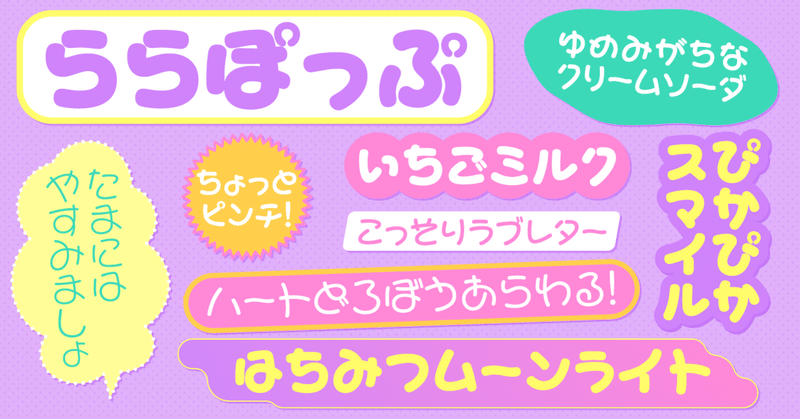
社会現象になった “丸文字” をルーツに持つ書体「ららぽっぷ」
1. 遊び心に溢れたデザイン
ららぽっぷはこんなデザインの書体です。
ららぽっぷは「新丸ゴ」の漢字と組むことを想定して作られた丸ゴシック系かな書体で、新丸ゴに合わせてL・R・M・DB・B・H・Uの7ウエイト展開をしています。(かな書体についてはこちらの記事をご覧ください!)
独特の崩し方をした骨格をもち、遊び心に溢れたかわいらしいデザインをしています。
細かい特徴を見ていきましょう
・有機的な曲線で構成されていて、丸い
全ての文字が直線を含まず、手書きで書いたような揺れのある曲線で構成されています。全体的なシルエットも丸く作られていて、かわいらしさを演出しています。
・ループが大きい
ループを持つ文字は、それが大きく強調されています。文字により丸い印象を与えていますね。
・独特な点の交差
本来接触しない点や線が他のパーツと交差していたり、突き抜ける線が短く接触しない形になっているものがあります。独特の崩し方を感じさせる要素のひとつです。
特徴、掴めてきましたか?
2. ルーツとなった社会現象 “丸文字”
ららぽっぷは2007年にリリースされた書体ですが、この独特の字形は1970〜1980年代に流行した “丸文字” という書き文字のスタイルを意識して作られた書体です。
1970年代後半から、女子学生の間で扁平で丸っこい、癖のある図形的な文字を書くことが一大ブームとなりました。ひらがなの丸い部分を強調したり、角のある部分を丸くして書かれることが多かったことから丸文字と呼ばれます。
当時丸文字を書いていたという弊社スタッフに、再現してもらいました。
それぞれの文字に丸を強調するような特徴があってかわいいですね...!(書いてくれたスタッフはデザイナーではない、というのもミソです)
当時流行していた交換ノートを中心に使う人が増加していき、500万人近くが丸文字を使用していたとも言われるほどです。「かわいい」や「女の子」の象徴として、社会現象になりました。
書体の世界にもその影響は押し寄せ、丸文字だけのデザインコンテストが行われ、入賞作品が書体化されたり、人気アイドルが手書きした丸文字が書体化されるなどしました。デザイナーではない人たちがタイプデザインをしていたと考えると、その影響力がどれほどだったのか考えさせられますね。
モリサワからも、丸文字を元にした書体がリリースされています。
現在はスマホの普及などから文字を “打つ” ことが多くなっていますが、1970〜1980年代は文字を “書く” ことが中心の文化だったとも言えます。その中で書き文字である丸文字が、人々の一種の自己表現にとどまらず、デザインの世界にも影響を及ぼしました。
3. 「ららぽっぷ」デザイナーインタビュー
ここからは、そんな特徴的な背景とデザインを持つららぽっぷの制作秘話に迫るべく、担当デザイナーへのインタビューをお届けします!
お話を聞いた人:タイプデザイナー 市川秀樹
プロフィール:1970年にモリサワ文研株式会社に入社し、写真植字機文字盤の制作に従事。1996年タイプデザイナーとして仮名や従属欧文の作成を開始。 これまでに、アンチックファミリー、UD新ゴ、黎ミングラデーションファミリー、A1ゴシックなど、多くの書体の仮名・記号類のデザインを担当。
ーまずはららぽっぷが作られた背景について教えてください。
市川:当時、ラインナップのバリエーションを増やすために新ゴや新丸ゴの漢字に合わせたかな書体を多く開発していて、その流れでできたのがららぽっぷです。様々なテイストのかな書体を開発する中で、飛び抜けてポップな書体としてつくりました。
ーなるほど。かな書体たちの中でも目を引く個性を持つららぽっぷですが、何か参考にしたものはありますか?
市川:実は、「わらべ」という書体が関係しています。わらべは1987年にモリサワからリリースされた写植用のかな書体です。丸文字が社会的ブームになった当時に作られた書体で、こんな見た目をしています。
ーららぽっぷによく似ていますね...!
市川:と言っても、ららぽっぷはわらべを元にしたのではなく、あくまで “わらべの制作時に集めた資料” を参考にして、新丸ゴに合う新しいデザインの書体として作られました。
丸文字風のフォントを作るにあたって、当時の社員が喫茶店を回って落書き帳のようなノートを借りて来たそうです。お店を訪れる人が自由に書き込めるもので、女子学生が丸文字でたくさん書き込んでいた。それを資料にしていました。
ー過去の資料を参考にしてららぽっぷが新しく作られたんですね!その資料を元に、どのように制作が進められたのでしょうか?
市川:ららぽっぷはかな書体ということもあって、基本的に私1人でデザインを担当しました。この書体はアナログに原図を書いて作成したわけではなくて、新丸ゴのデータをそのまま活用して作りましたね。
ー新丸ゴのデータをそのまま!何か理由があったんでしょうか。
市川:新丸ゴに合わせて7ウエイトのファミリー書体になる予定だったので、太みを合わせるという意味がひとつ。もうひとつは、新丸ゴの先端を使いたかったんです。丸ゴシックの先端は名前の通り丸いのですが、まんまるかというとそうではなく、微妙に扁平ぎみな丸みをおびています。
ー確かに、書体によって少しずつ丸みが違いますね。
市川:丸ゴシックを作る時、この先端の丸みや形をどうするかというのはすごく難しいことなんです。ららぽっぷは新丸ゴのかな書体として統一感を持たせるために、新丸ゴの先端を使って制作しました。比べてみると似てるんじゃないかな
ーかな書体として、合わせる書体と統一感を持たせる工夫が必要だったんですね。ところで、個性的で当時の「女の子の文字」の側面が強い丸文字。市川さんに馴染み深い書き文字ではなかったのではと思うのですが、難しさはありましたか?
市川:うーん、確かに個性的な形ではあったけど、文字の形をかなりポップに振り切った書体だったから、逆にそこまで迷わなかったですね。オーソドックスなものを作ろうとする方が、既存のものに引っ張られてしまって難しかったりします。
ー個性が強いからこそ、思い切ってデザインできる面もあったんですね。では、ららぽっぷを作る際に苦労したこと、難しかったことはありますか?
市川:苦労したのは、やはり新丸ゴの漢字に遊び心のあるかなを合わせることです。新丸ゴは字面が大きく仮想ボディいっぱいにデザインされているので、かなも他書体と比べてやや大きめに設定し、できるだけ漢字との親和性が高まるように調整しました。
市川:あとは、新丸ゴに合わせて7ウエイト作ることも難しかったですね。L ~ Uまで統一したイメージを展開するために、ただ線を太くしていくだけではなく、多くの調整が必要でした。
ー新丸ゴと合わせるかな書体として考えなければならない部分が多かったんですね...。
市川:一番苦労したのは可読性を保つこと。実際に流行していた丸文字の形をそのまま採用すると読みにくくなってしまうものもあったので、デザインをチェックして吟味する必要がありました。
これは、ひらがなのデザイン確認に使用した文章組出力見本の一部です。
ーいろいろな童謡が並んでいますね。
市川:当時は制作途中のものをすぐにデジタルフォント化することができなかったので、決まったフォーマットに流し入れて確認する形でした。これはかな書体用のフォーマットですね。文字数がある程度揃わないと確認ができないのが大変でした。今はフォント制作エディタの中で文字を自由に並び変えたり、すぐ手元でフォント化することができるので、すごく自由に確認ができるようになったなと思います。
ー様々な条件で可読性をチェックし、デザインを整えることが重要かつ難しいことなんですね。
市川:可読性はもちろん追求していく必要があるのですが、ららぽっぷのように少し崩れたバランスを持つ書体はあまり整えすぎてもいけない、という面もあるので特に難しかったですね。
4. おわりに
丸文字を参考に作られたららぽっぷは、パッケージや店頭ポップなどでデザインのアクセントとして個性を発揮するのはもちろん、近年人気が高まってきている昭和レトロな表現にも活用できるのではないかと思います。